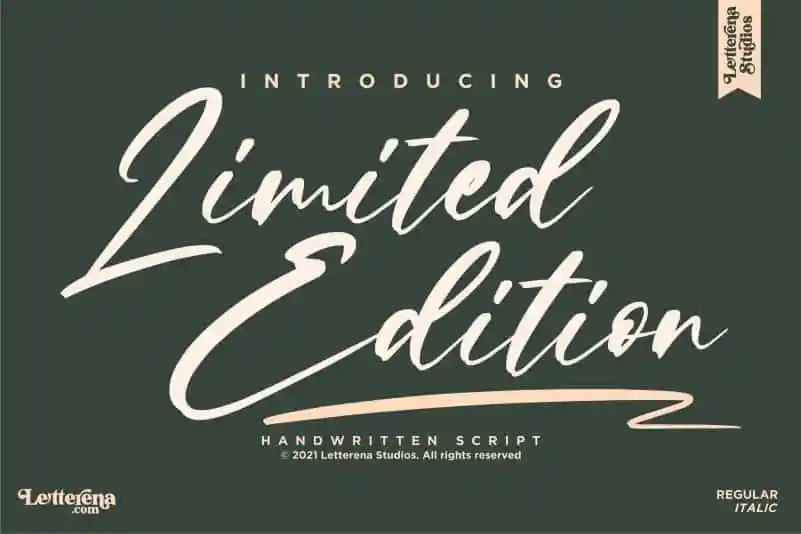
Limited Edition Script Font – Download Grátis
A fonte ‘Limited Edition Script Font’, criada pela Letterenastudios, é uma opção perfeita para aqueles buscando adicionar elegância e sofisticação a seus projetos digitais ou impressos. Esta fonte script romântica é ideal para um vasto leque de aplicativos, desde desenhos de logotipos e criações de marca até designs de embalagens, selos e mensagens personalizadas. Sua versatilidade permite que você personalize suas criações em uma variedade de objetos, incluindo tênis de sapato, etiquetas para garrafas, capas de livro, adesivos de lembranças, materiais promocionais, e até mesmo rótulos de caixas de foto. Seja qual for o projeto que você está trabalhando, a ‘Limited Edition Script Font’ tem uma opção adequada para ajudá-lo a alcançar um toque personalizado e sofisticado. Com uma paleta de recursos vasta e flexível, esta fonte é certamente a escolha perfeita para qualquer projeto de luxo que precise de uma autêntica escrita de papel para dar seu trabalho uma cara única.